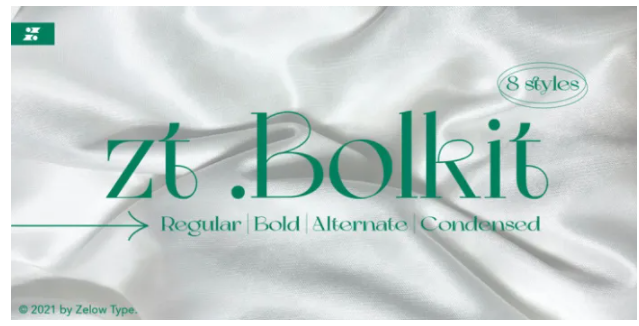
zt. Bolkit Serif - это шрифт с двумя типами стилей, один из которых имеет элегантную и плавную форму арки, а другой - тип твердости, и в нем представлен сильный характер. Будучи шрифтом, концепция которого очень заинтересована в простоте, линии, присутствующие в элегантном и твердом zt. Bolkit заставляют почувствовать это и вас.
zt. Bolkit также поставляется с двумя вариантами ширины, которые имеют два веса (тонкий и жирный). Содержит символы, которые включают прописные буквы, строчные буквы, цифры, пунктуацию, 52 лигатуры, 25 альтернатив и символы, которые сделают ваши дизайны круче в будущем. Не забывайте также, что он поддерживает более 60 языков, происходящих от латыни, а именно западные, центральные и юго-восточные европейские языки.
zt. Bolkit Serif - это шрифт с двумя типами стилей, один из которых имеет элегантную и плавную форму арки, а другой - тип твердости, и в нем представлен сильный характер. Будучи шрифтом, концепция которого очень заинтересована в простоте, линии, присутствующие в элегантном и твердом zt. Bolkit заставляют почувствовать это и вас.
zt. Bolkit также поставляется с двумя вариантами ширины, которые имеют два веса (тонкий и жирный). Содержит символы, которые включают прописные буквы, строчные буквы, цифры, пунктуацию, 52 лигатуры, 25 альтернатив и символы, которые сделают ваши дизайны круче в будущем. Не забывайте также, что он поддерживает более 60 языков, происходящих от латыни, а именно западные, центральные и юго-восточные европейские языки.